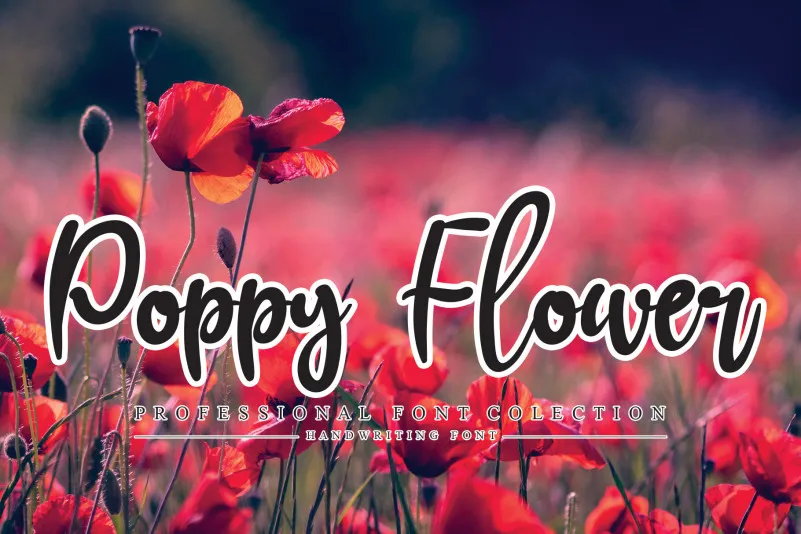
A Poppy Flower Script Font é uma elegante e suave fonte escrita a mão que traz com ela uma mistura única de influências clássicas do xarope e frescura contemporânea, criando um design atemporal. Suas linhas delicadas contornam o olhar sem deixar de lado as nuances sutis da tipografia tradicional, mantendo seu charme enquanto se atualiza para o século atual. Este estilo suave e romântico é perfeito para aqueles projetos que desejam transmitir uma sensação de serenidade e delicadeza ao mesmo tempo em que trazem um ar moderno à sua arte digital. Descubra a magia da Poppy Flower Script Font – ela vai transformar seu trabalho nas alturas!